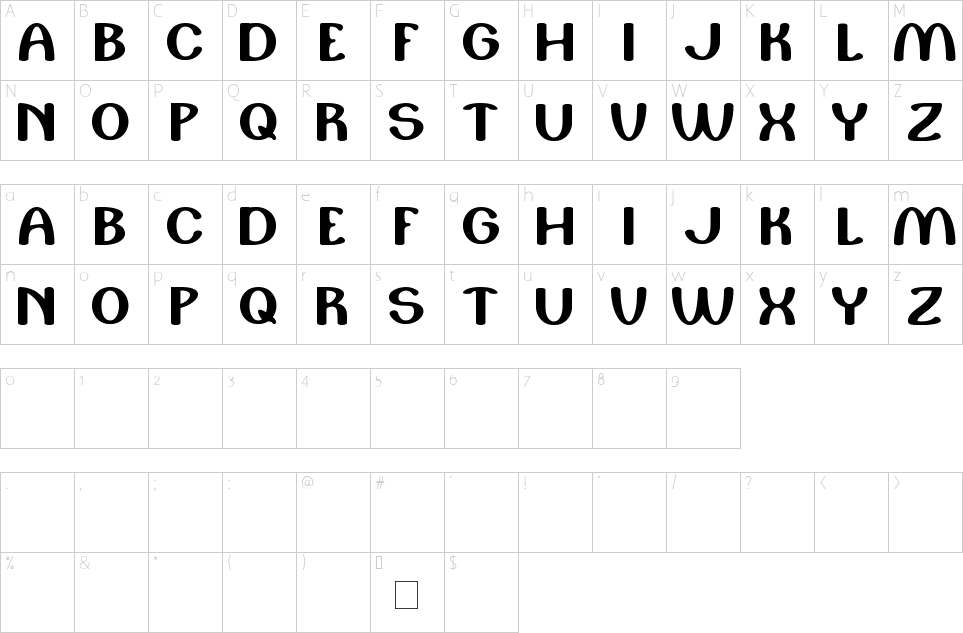
A fonte Play The Game é uma ótima escolha para aqueles que buscam um visual descontraído e divertido para seus projetos digitais. Desenvolvida por weknow, esta fonte vem inspirada nas tramas de jogos memoráveis que muitos de nós tivemos no passado. Se você está procurando por uma fonte versátil que pode ser usada em um amplo range de aplicações, Play The Game é uma opção excelente. Mais de 3.700 pessoas já baixaram esta fonte, o que evidencia seu potencial para tornar seus projetos únicos e divertidos. Para os que buscam diversão na web, esta fonte é uma ótima adição para seus designs. Sem dúvida, Play The Game é uma escolha adequada para aqueles que desejam criar mensagens alegres e vivas.